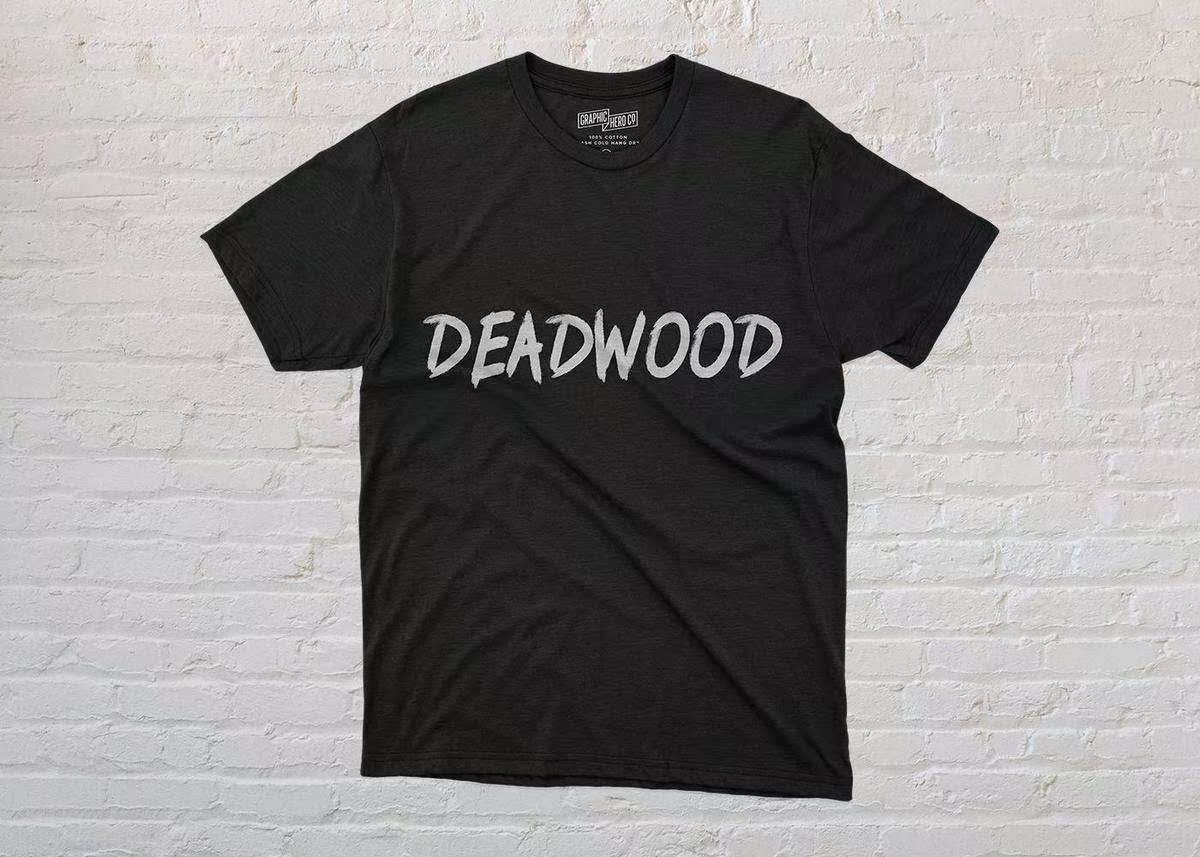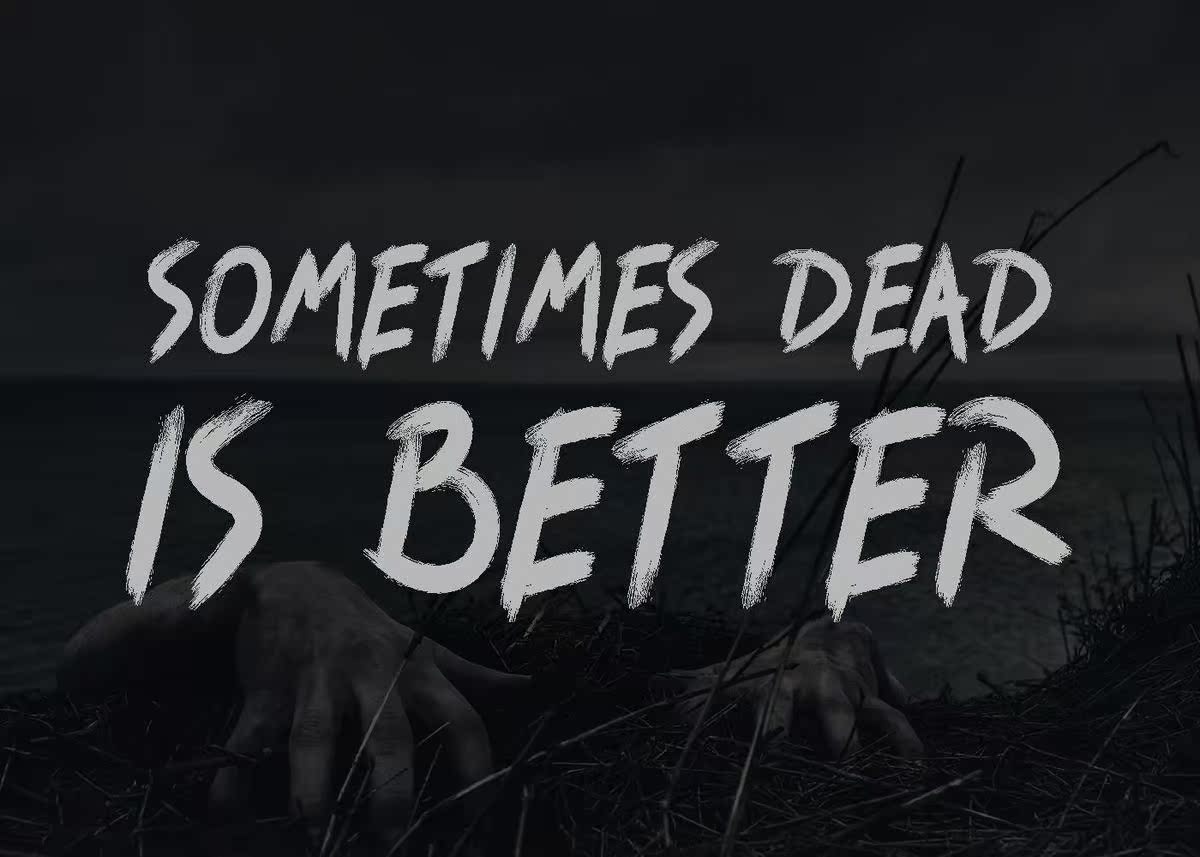
ZombieHolosuitisHandDeAuthenticationFontBrushWithTylishLooksKeeXtremorStyleUsage。徽标、标题、标题、印刷品、服装和其他创造性加工可能性的最佳匹配。ZombieHolosuisHandDeAuthenticationFontBrushWithTylishLooksKeeXtremorStyleUsage。徽标、标题、标题、印刷品、服装和其他创造性加工可能性的最佳匹配。